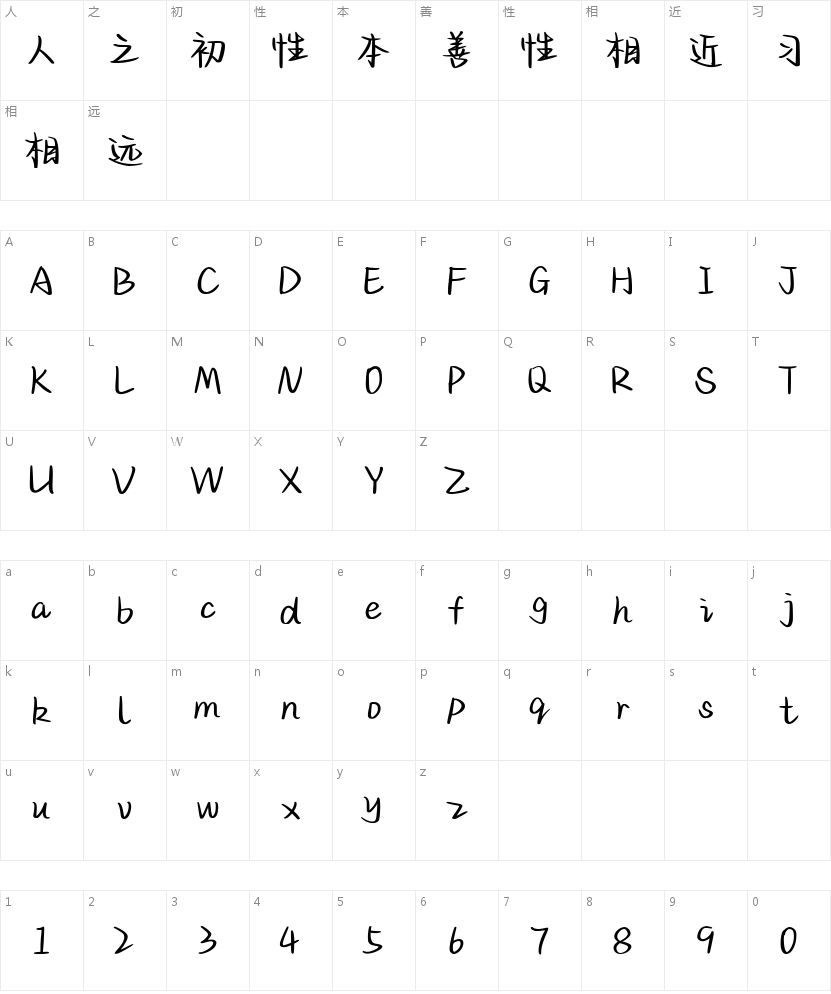
"我在5点23分想你"字体是一种流行的手写字体,其灵感来源于情感和爱情。这种字体的特点是优美、流畅和柔和,可以表达出深情和温暖的情感。这种字体通常用于制作明信片、情书、爱情故事等场合,以表达出对特别的人的思念和爱意。如果你想要表达对某人的情感,这种字体是一个非常不错的选择。内容介绍
我在5点23分想你是一款非常不错的手写艺术字体,具有很好的视觉感,适合于文化类的宣传设计、商业类品牌的广告和产品包装设计以及个性化文字排版等较多场景。